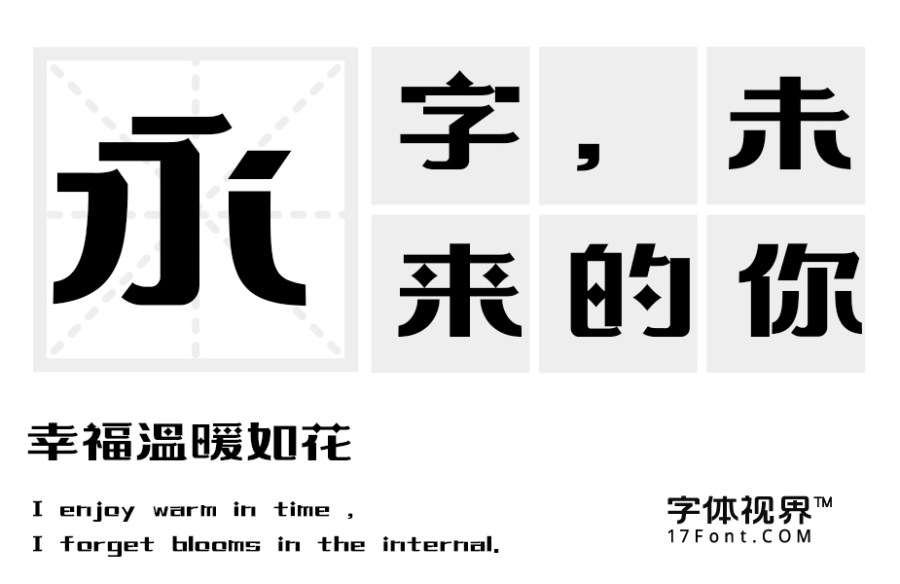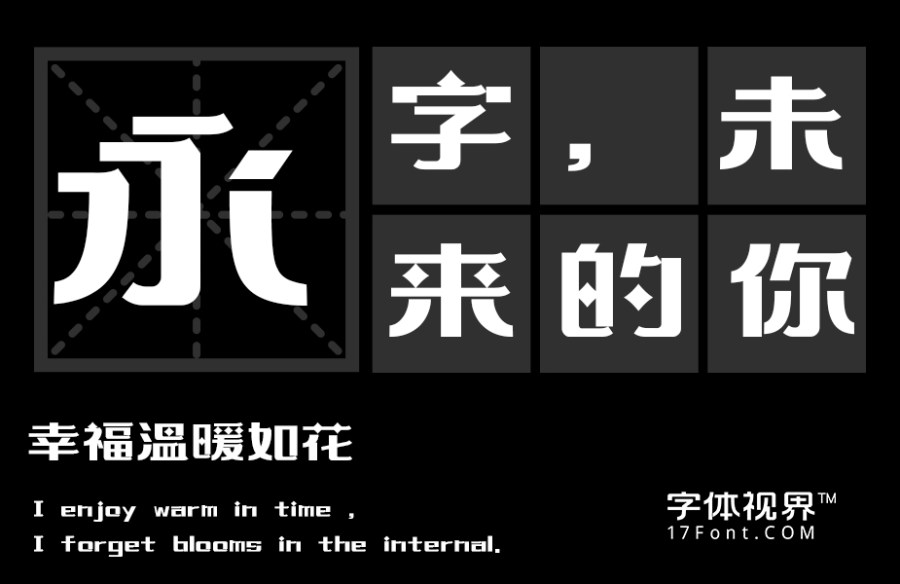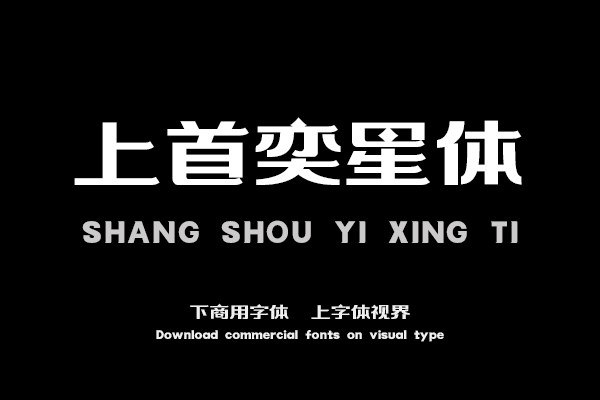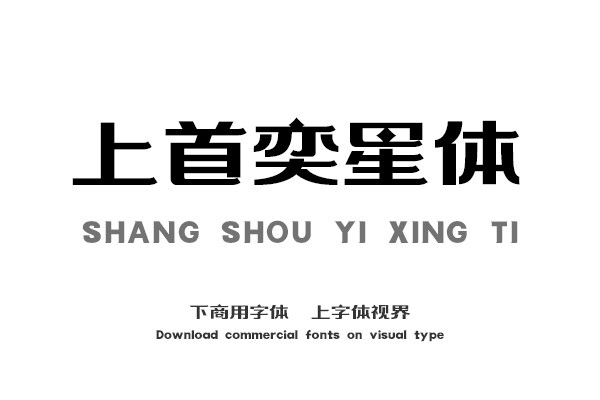
上首奕星体,简体中文约6763字,字体笔画流畅,横竖笔进行了改良,整体直线处理,字体笔画简洁,形态苍劲有力 加上四面内凹的点状特点。 适用于搭配标志、广告标语、......购买须知:“下载服务费”与“字体VIP”所获得字体 仅用于个人非商用, 商用请联系付费授权。本字体为电脑用字,手机没有root权限不支持直接手机换字(手机如何root,请自行百度搜索教程)。购买前请先 了解清楚后再付款 ,字体为虚拟产品无法回收 一旦购买不支持退款。